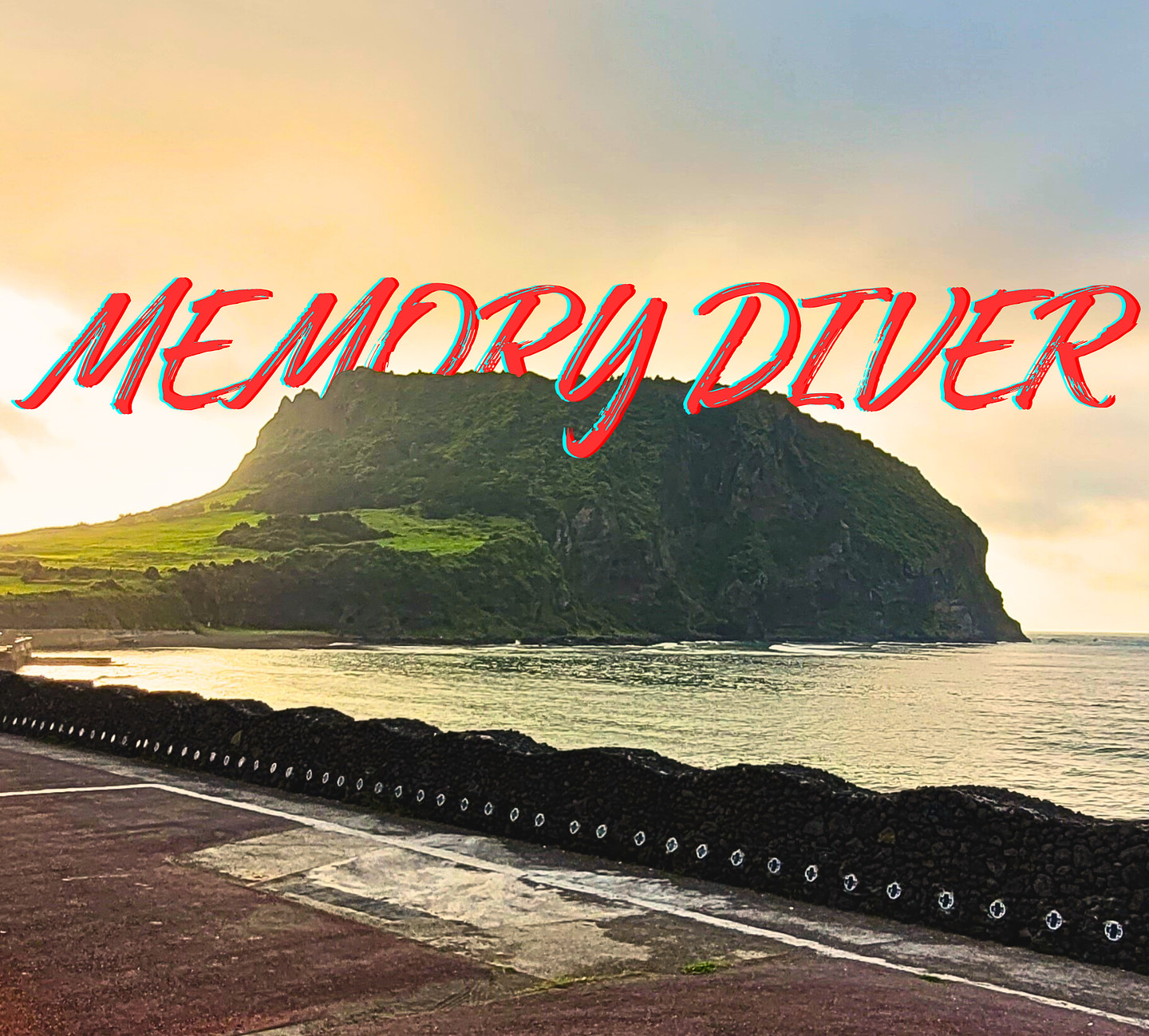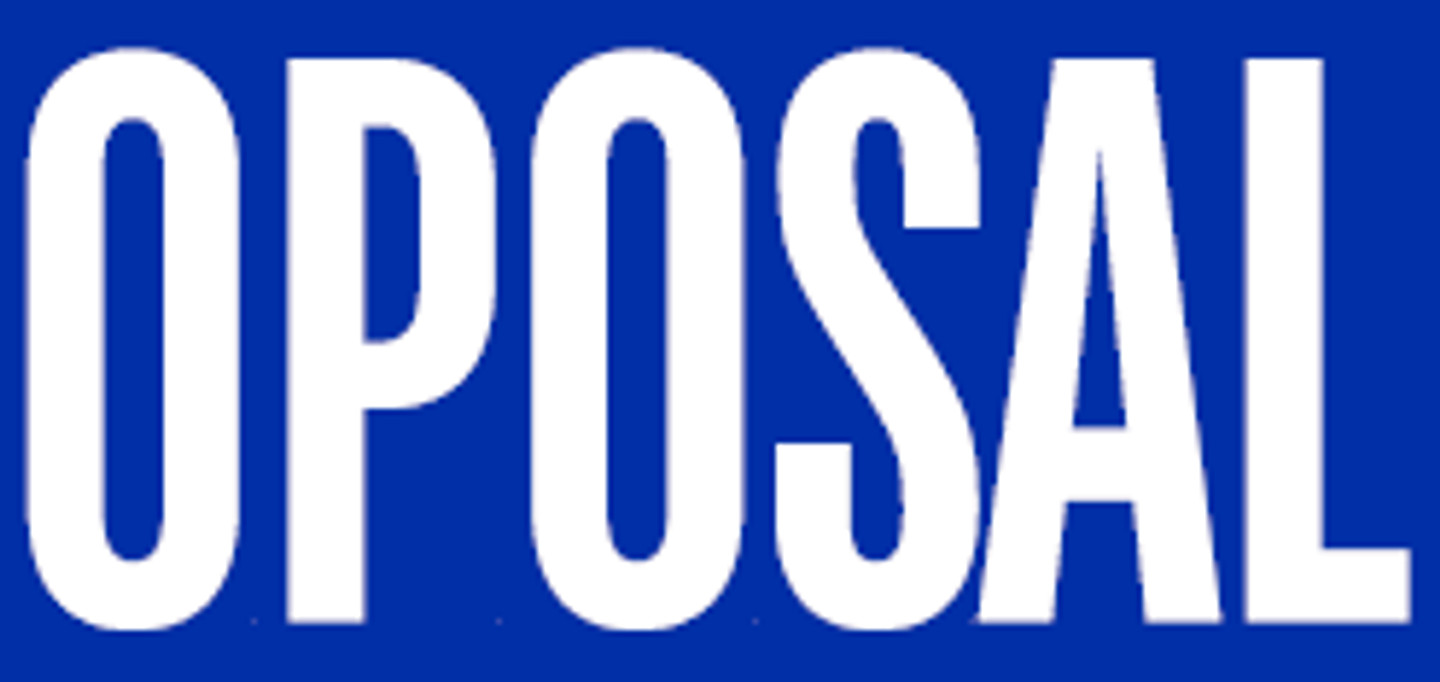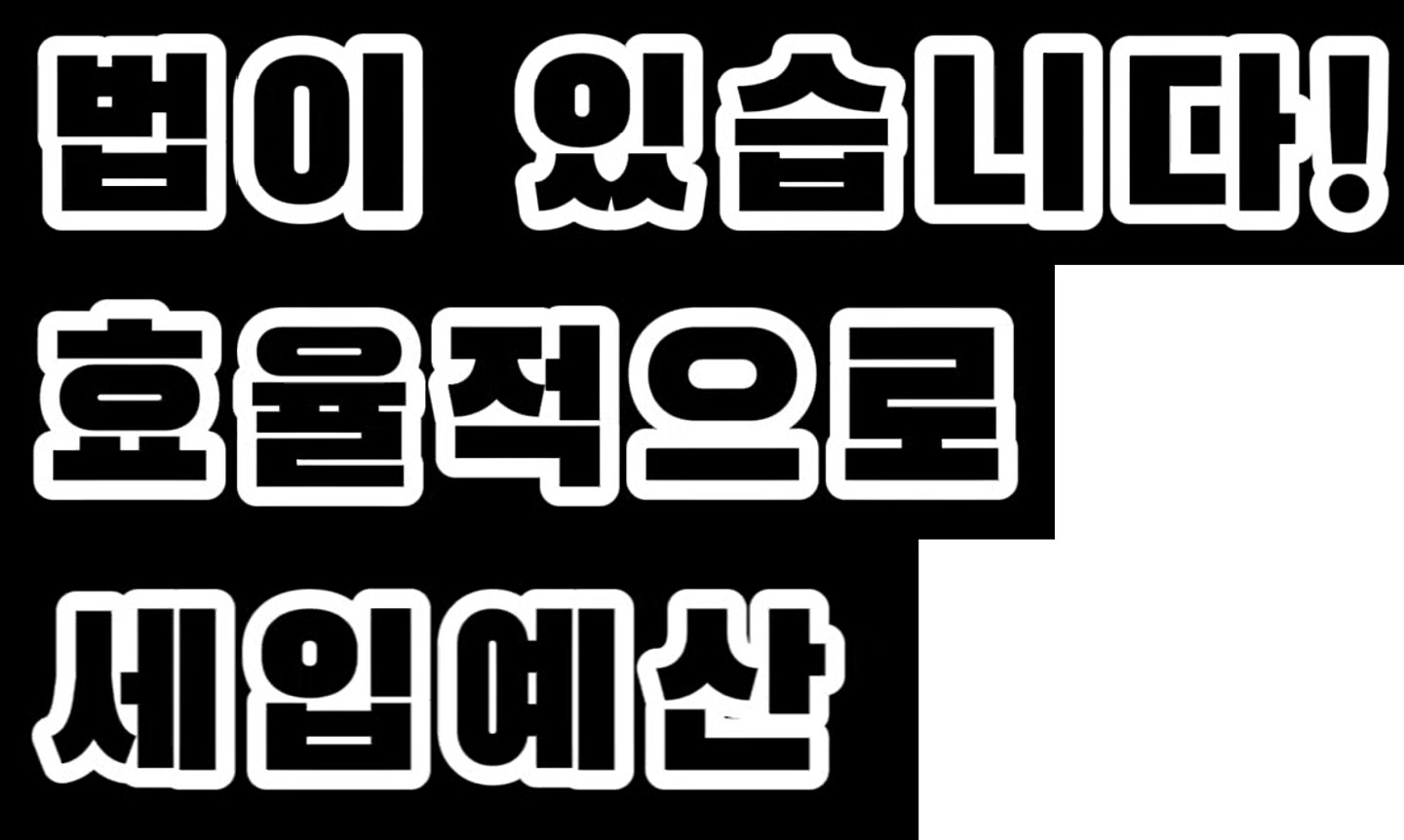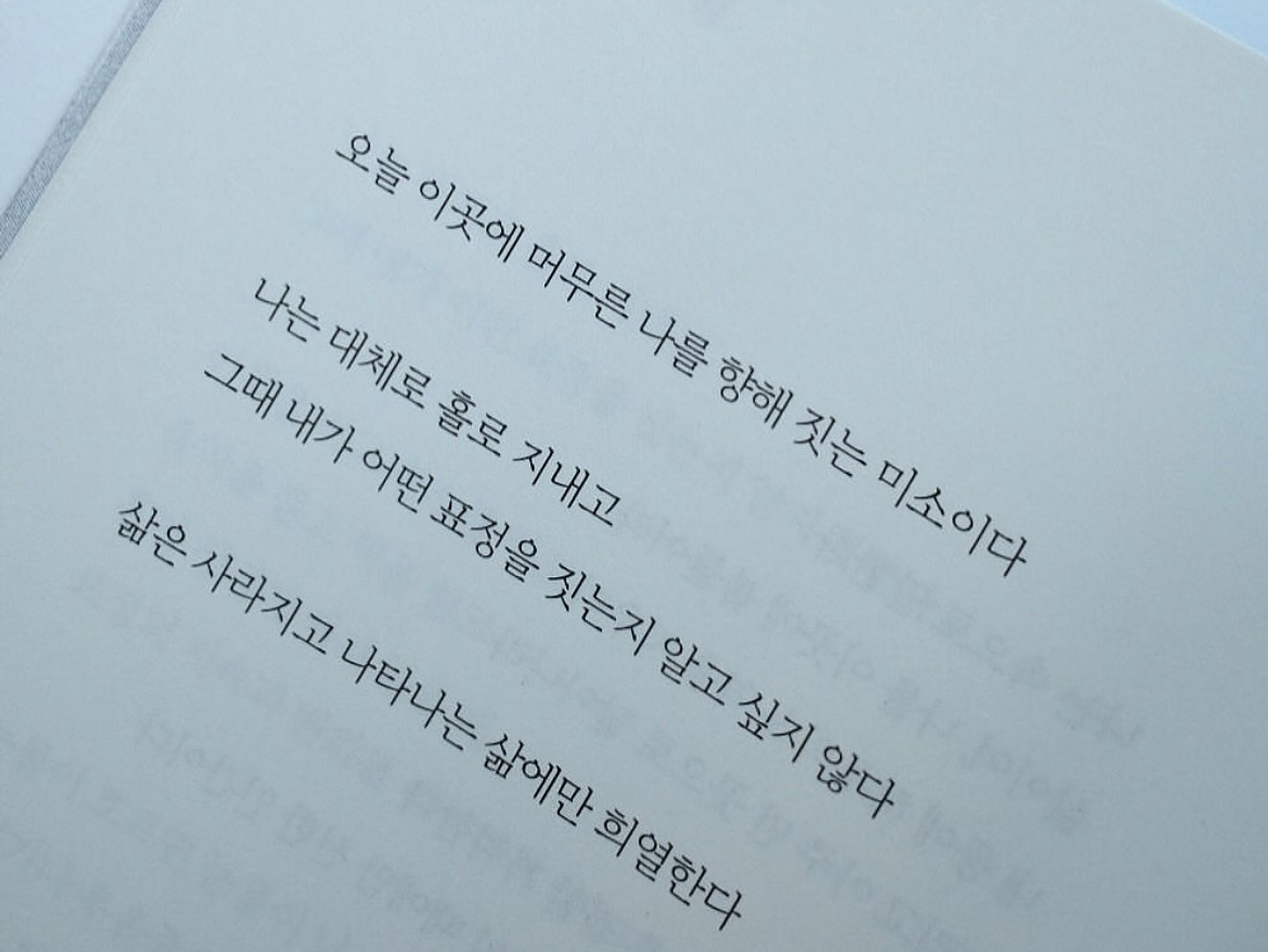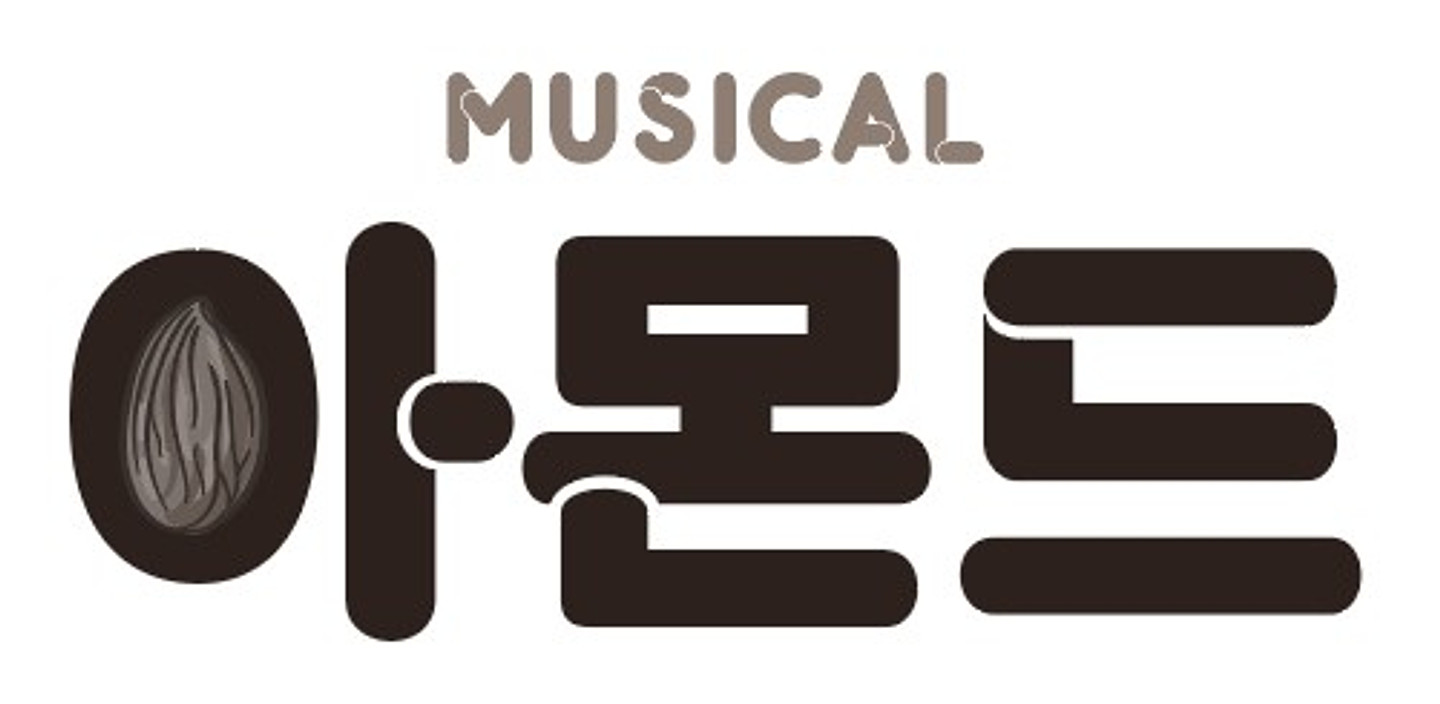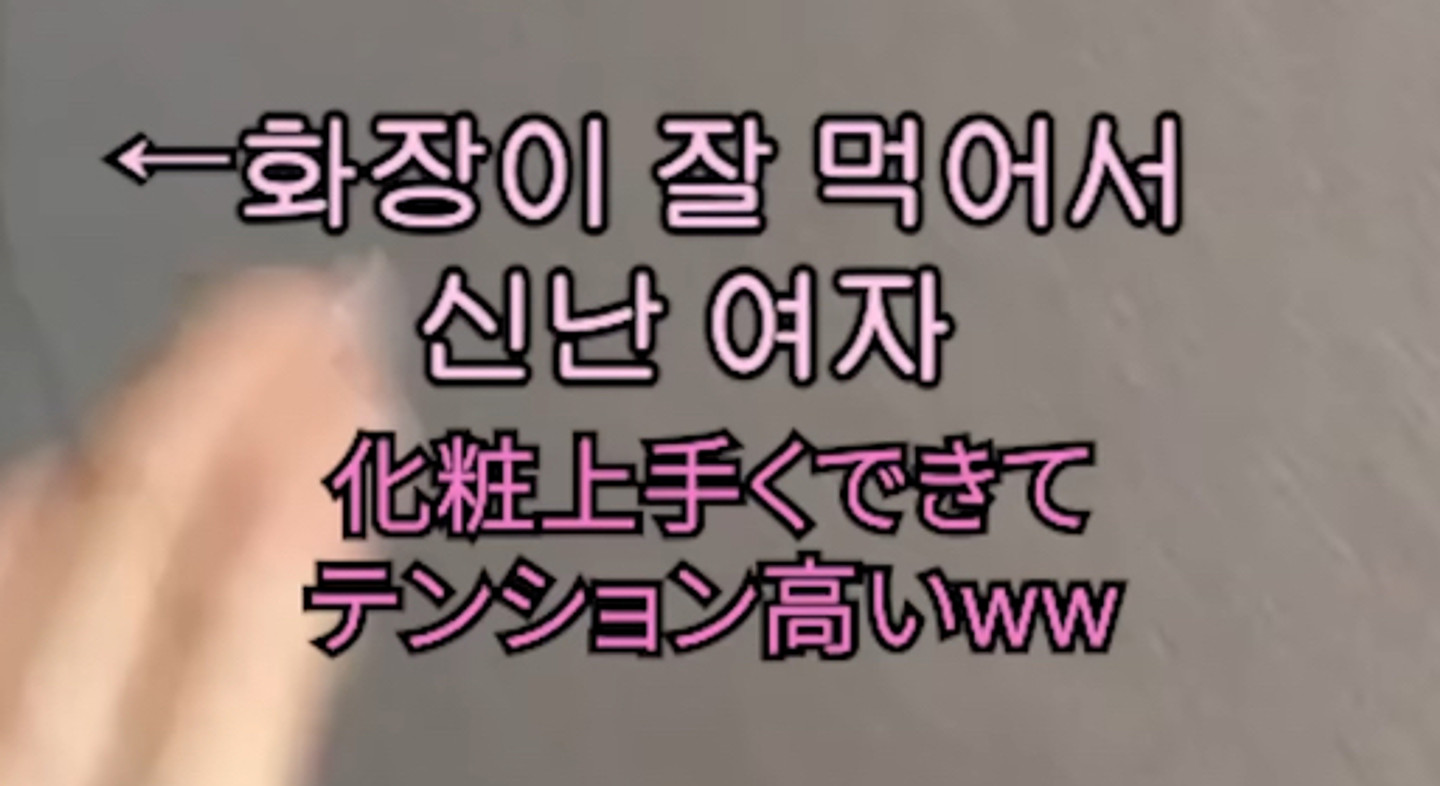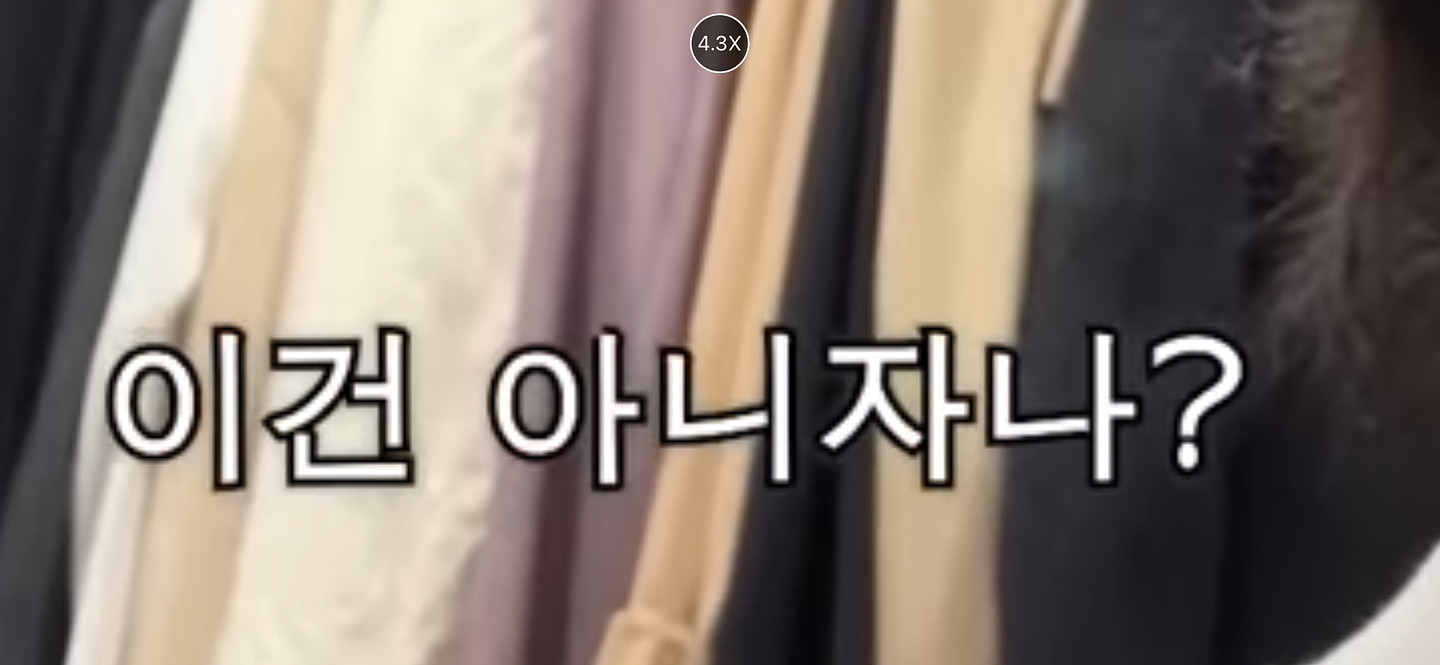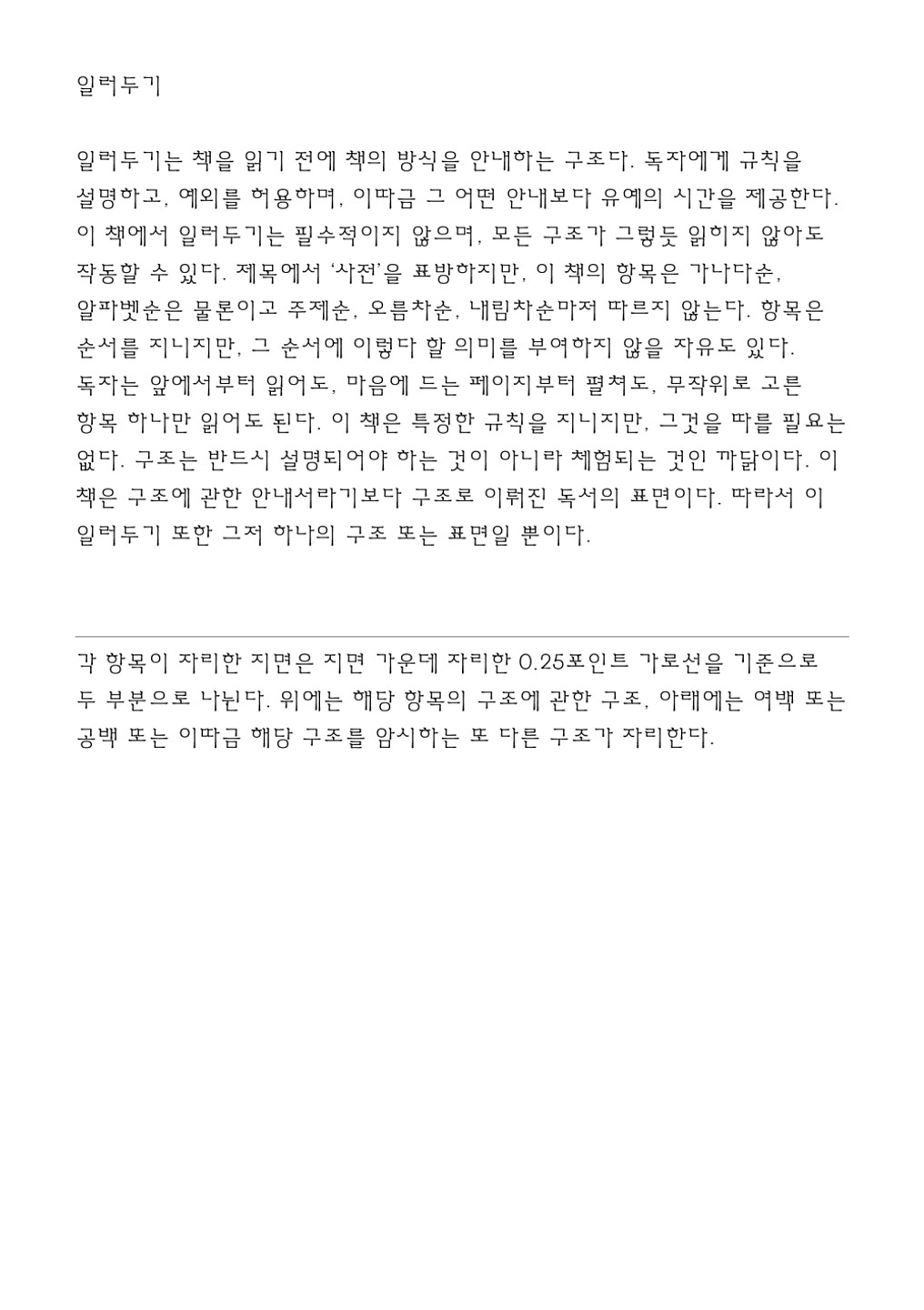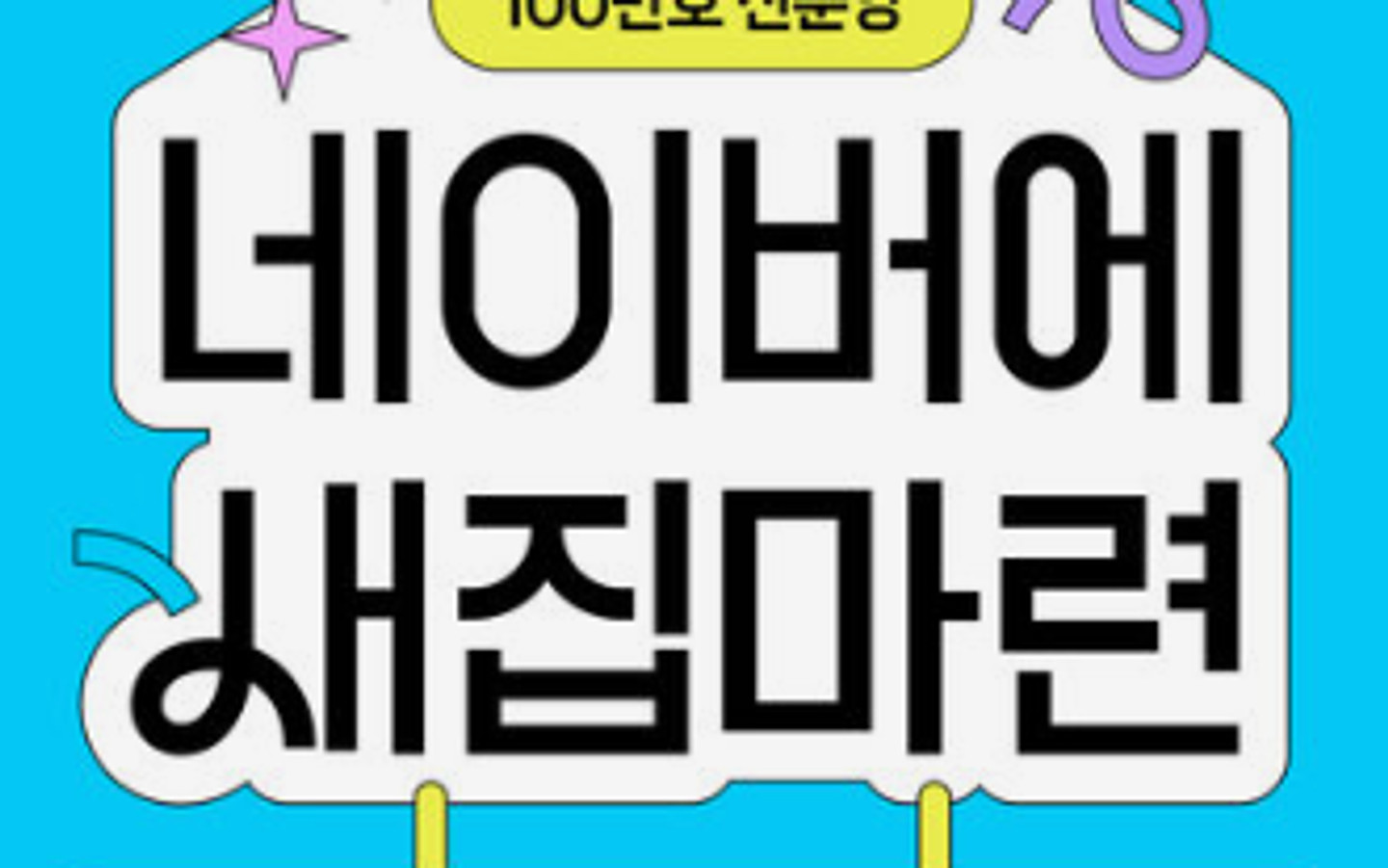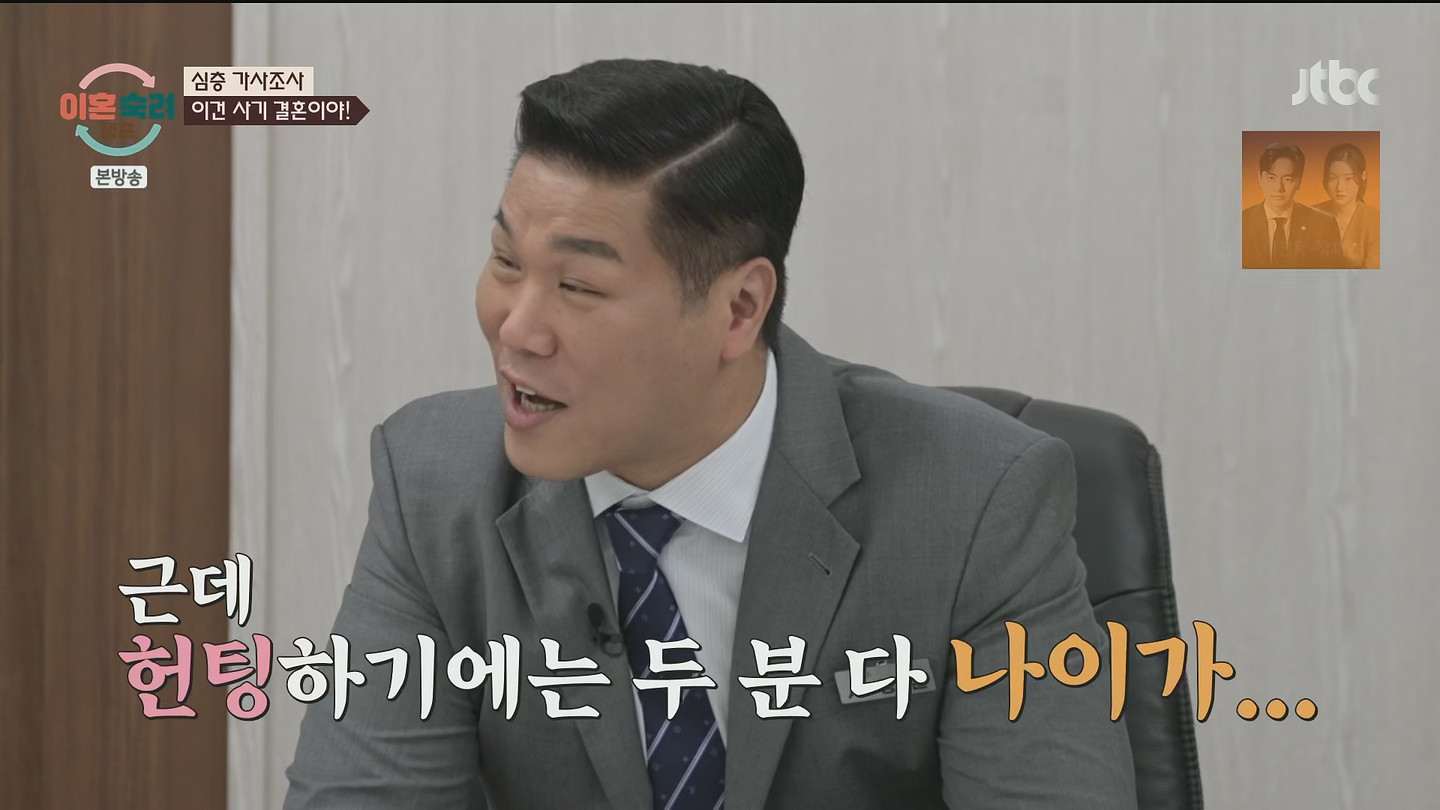
yes24 미리보기에서 발췌한 공개된 본문 스크린샷입니다. 김영사 출판사의 '오독의 발견' 이라는 책의 본문에서 사용된 폰트입니다!
폰트 궁금합니다!!!
이거 이름 뭔가요
이거 뭔가요
이게 무슨 폰트인지 알 수 있을까요?
알파 오메가 폰트랑 주황 영어 폰트가 뭔지 알수 있을까요?
유튜버 빨강도깨비님이 사용하시는 폰트 인데 아무리 찾아봐도 없어 질문드립니다.
이 폰트 혹시 아시는 분 계신가요?? 정확한 폰트 알려주시면 좋은데 비슷하게라도 알고 계신 분 계시면 꼭 답변 부탁드립니당ㅠㅠ
고독한 미식가에 나오는 약간 기울여 진 동글동글한 글씨체는 뭔가요 감성계 브이로그 YouTube에서도 많이 보이더라구요
이 폰트 모에용?
위에 자막이랑 아래 자막 폰트 2개 다 궁금합니다 !!
뮤슨 폰트야?
옆으로 기울어져있는데 몽글거리는 이 폰트는 뭘까요? 너무 기여움!!!
폰트뭐ㅔ요?
글씨체가 뭐지?
이 폰트가 뭔지 알수 있을까요?
이거므ㅓㄴ지 아시는분,,,,비슷한건 꽤 많은데 저런 느낌이 안나서요
유튜브에서 본 자막 폰트인데 뭔지 궁금하네요 ㅠ
임의로 만든 이미지 인데 폰트가 궁금합니다
이 폰트 뭔가요
이 폰트 무슨 폰트인지 알수있을까요?
가운데 시네타운 이라 적혀있는 글꼴이 긍금핮니다
안원잘부 채널 썸네일 텍스트 폰트가 뭘까요..?
이거 뮤슨 폰트인지 궁금합니다,,
이 책을 읽는 분들께 무슨 폰트일까요?
혹시 이 폰트가 어떤 서체인지 여쭤봐도 될까요?
이거 폰트 뭐에요?
동글동글한 귀여운 폰트인데.. 이름이 뭘까요 ㅜㅜ
이거 어떤폰트일까요??
어떤 폰트인지 궁금합니다.
osu에 나오는 폰트인데 무슨 폰트일까요
무슨폰트인가요
이 폰트 무슨 폰트죠??
소나무 글씨랑 밑에 영어랑 소나무과 글꼴 뭔지 알 수 있을까요 ㅠㅠㅠ
사진에 있는 폰트 문의드립니다
이 숫자와 같은 폰트나 비슷한 느낌의 폰트 좀 알려주세요 ㅠㅠ; 봐주신 분들 정말 감사합니다.
무슨 폰트일까요? 자주 봤던 건데…
장마철 실내식물원 이 글자 폰트 뭘까요? 너무 예쁜데 ㅠㅠ 눈누에서 찾으려니 힘들어서요
상세페이지 보다가 폰트가 이뻐서 이거 무슨 폰트인가요?
광고에서 나왔는데 이 폰트가 뭘까요오오
글씨체 궁금해요~!
저 폰트는 위아래로 늘린거로 아는데 저거랑 비슷한 폰트 있을까요 ㅠㅜ
쇼츠에 많이 나오는 글씨체 같은데, 어떤 글씨체 일까요? ^^;
혹시 해당 폰트 어떤건지 알 수 있을까요 ??
이거 무슨 폰트일까요 ㅠㅠ 오늘까지 마감이라 급한데 도와주세요 ㅠㅠ
이 폰트 뭔지 알 수 있을까요ㅠ 리센느 원이 유튜브 거제 1편에 쓰인 폰트입니다
무슨폰트인가요?~ 알려주시면 진심으로 감사드리겠습니다. 감사합니다 ^^ 즐거운 주말되세요